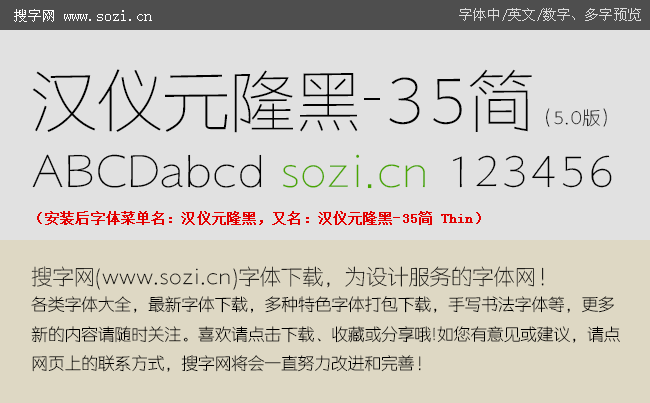
漢儀元隆黑-35簡(jiǎn)
搜字網(wǎng)提供一款漢儀元隆黑-35簡(jiǎn)藝術(shù)字體下載。大家習(xí)慣將漢字寫(xiě)得"右傾"和"上挑",這似乎是絕大多數(shù)人對(duì)于"端正"字的主觀理解和心理修正。元隆黑系列基于上述原由將字的橫筆畫(huà)設(shè)計(jì)為逐漸上挑的狀態(tài),使原本嚴(yán)肅、緊張 的黑體字在一定程度上親切、輕松甚至是俏皮的形態(tài)。適合畫(huà)冊(cè)標(biāo)題、海報(bào)設(shè)計(jì)、廣告宣傳等場(chǎng)合使用。